今回は「談」の書き方を解説します。
「談」の見本
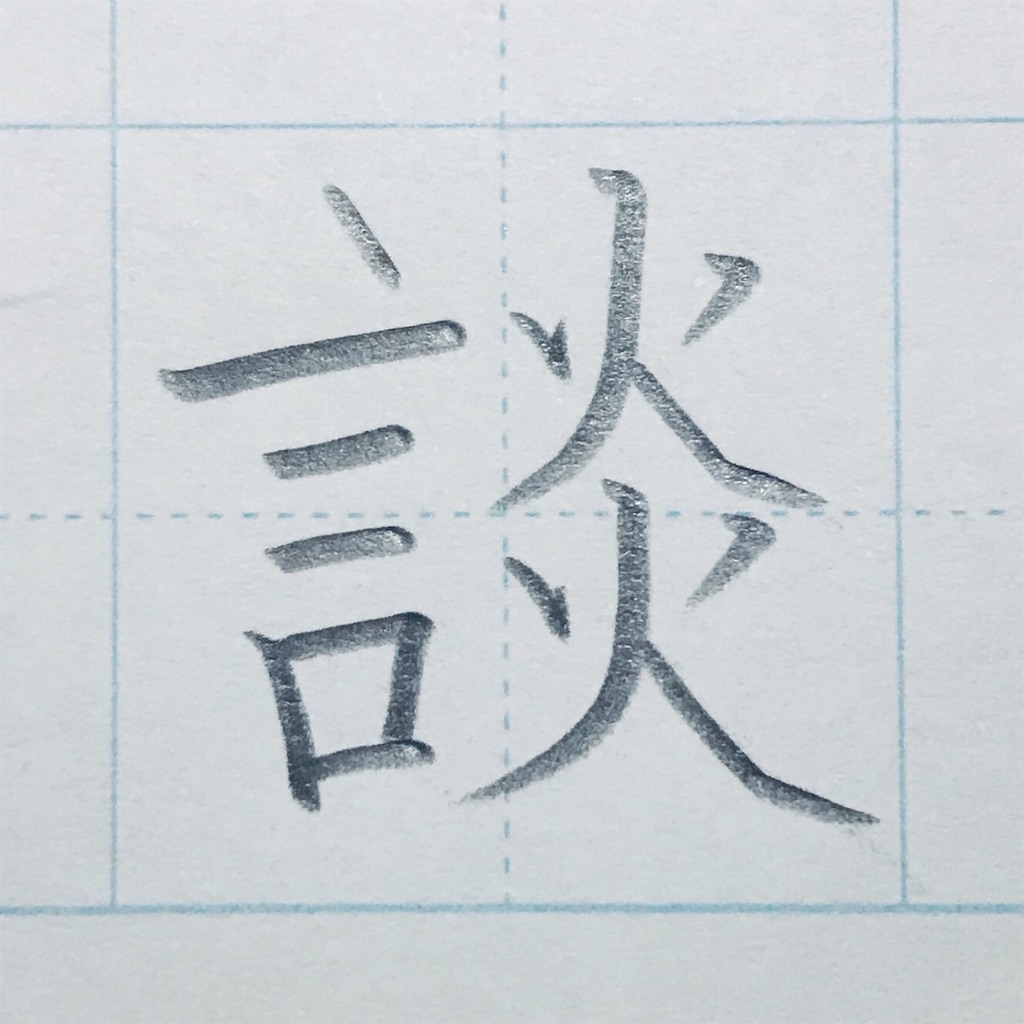
「談」の画数
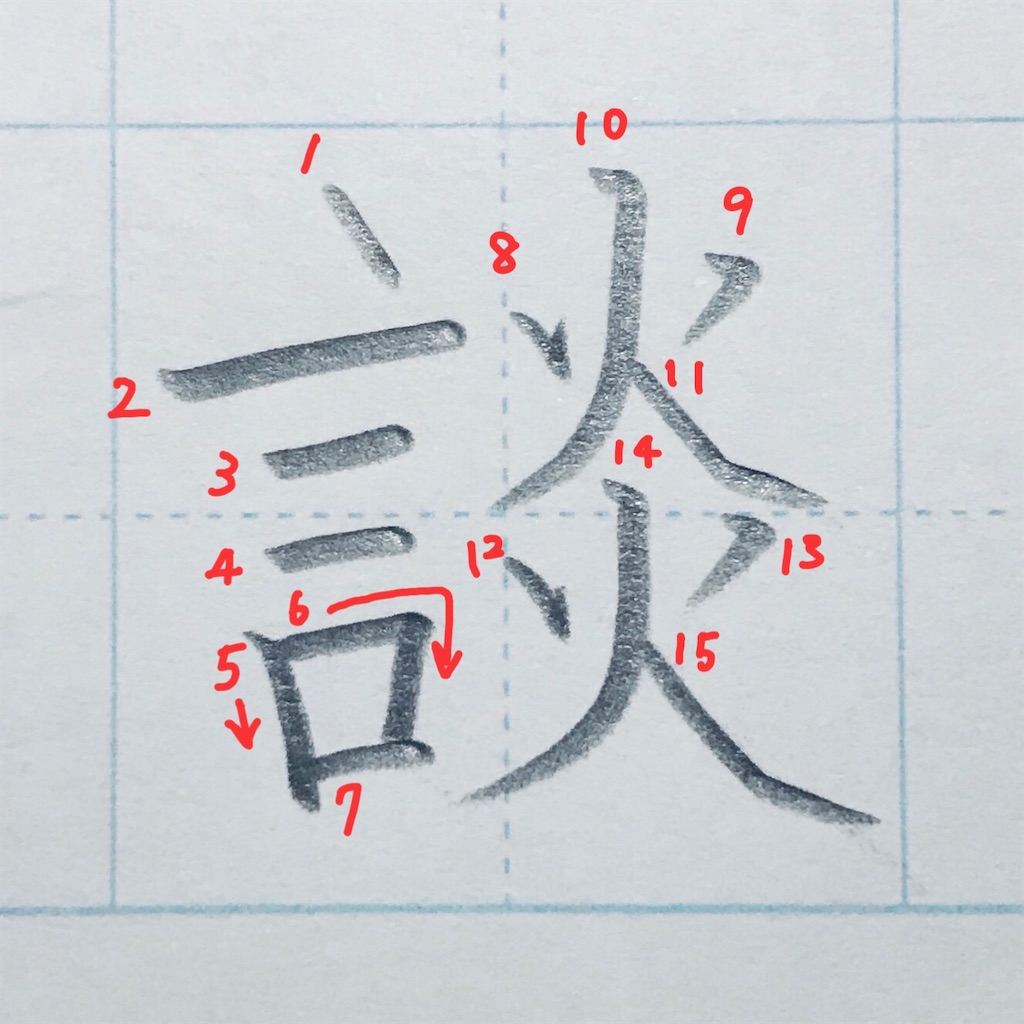
15画です。
「談」のポイント
①ごんべんは1画目の最初を基準に、真っ直ぐ書くのが大切です。
②2画目は、左側を長く出します。
③間を等しくします。
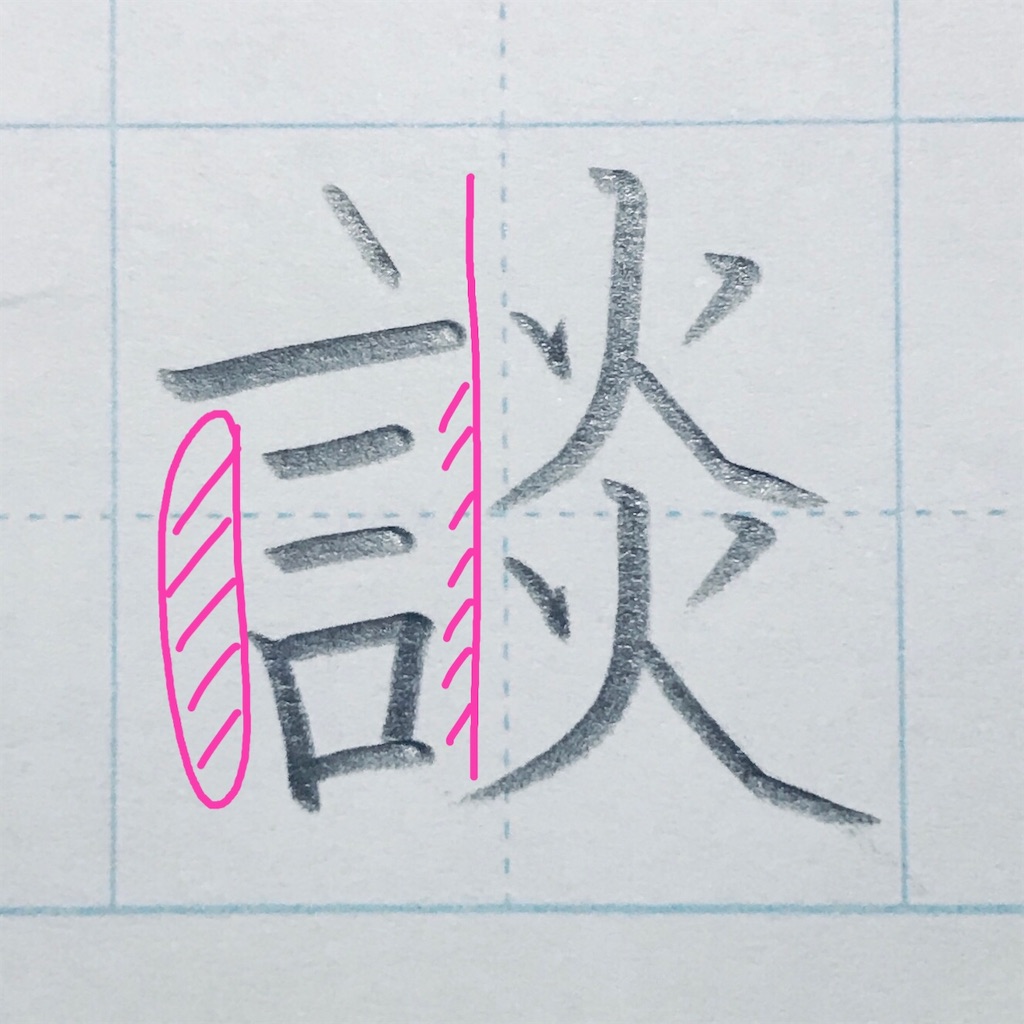
左側に余白を作る。右端は中心より少し左で揃える。
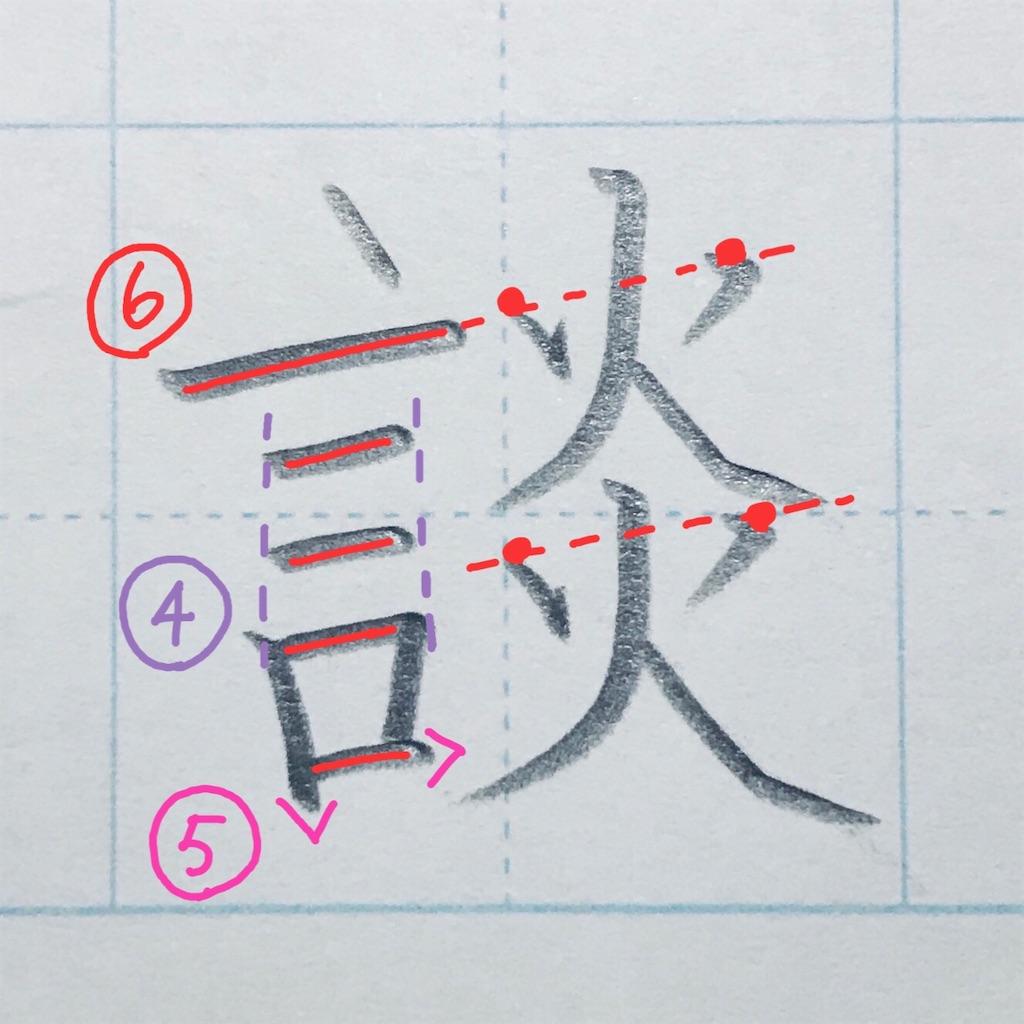
④3画目からは、幅を揃えます。
⑤縦画と横画を出します。
⑥横画は右上りに揃える。
「火」の1、2画目も一緒に右上がりにすると良いです。
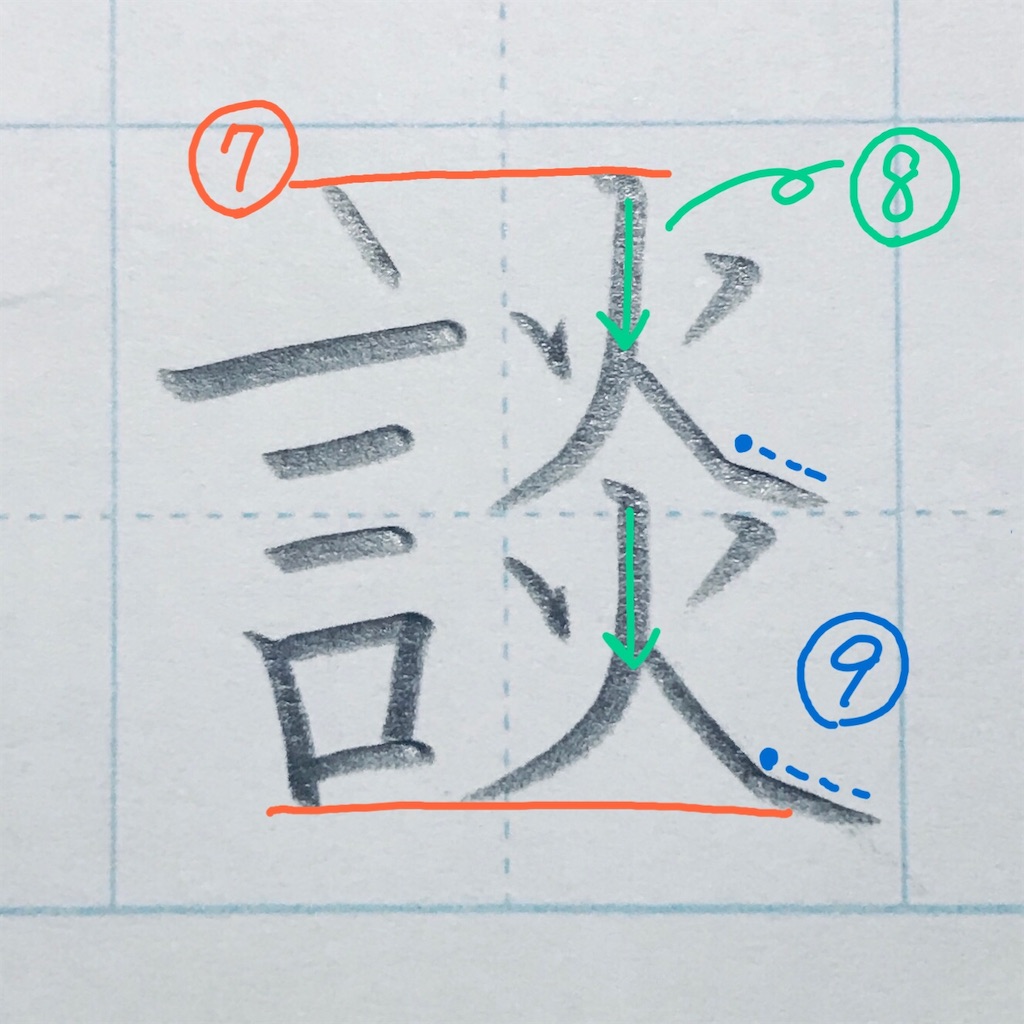
⑦上下の高さをだいたい揃える。
⑧「火」の3画目は半分くらいまで真っ直ぐにします。
⑨止めて、払います。
完成!